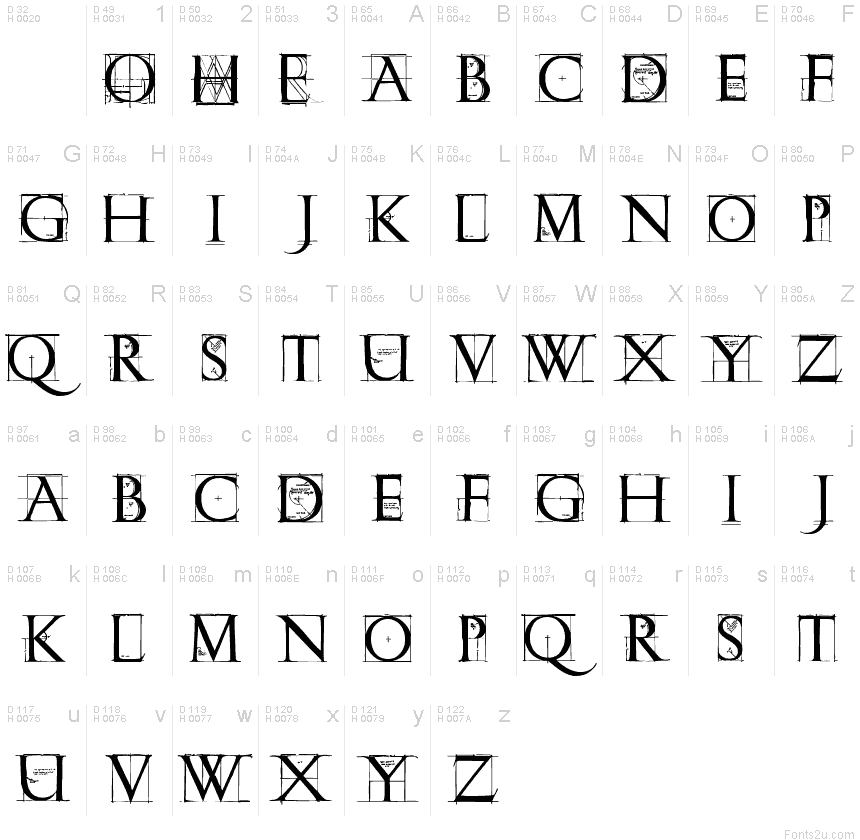
Roman Grid Caps autorstwa M. Klein to darmowy, utrzymany w stylu retro-techno krój typu display, który traktuje klasyczne rzymskie litery niczym rysunki techniczne z pracowni kreślarskiej. Litery łączą ostre, klinowe szeryfy i dostojne proporcje z widocznymi liniami konstrukcyjnymi, znacznikami i pomocniczymi miarkami, dzięki czemu krój przypomina jednocześnie starożytną inskrypcję i techniczny projekt.
Ta kombinacja świetnie sprawdzi się w tytułach plakatów, brandingu architektonicznym, grafice muzealnej, okładkach książek i planszach tytułowych, wszędzie tam, gdzie liternictwo ma nieść ze sobą przemyślany, inżynierski charakter. Jako darmowy font, sprawdzi się również w monogramach i krótkich nagłówkach, ponieważ wbudowane siatki konstrukcyjne sprawiają, że nawet kilka liter wygląda na starannie zaplanowane, wykreślone i narysowane z dbałością o detal.